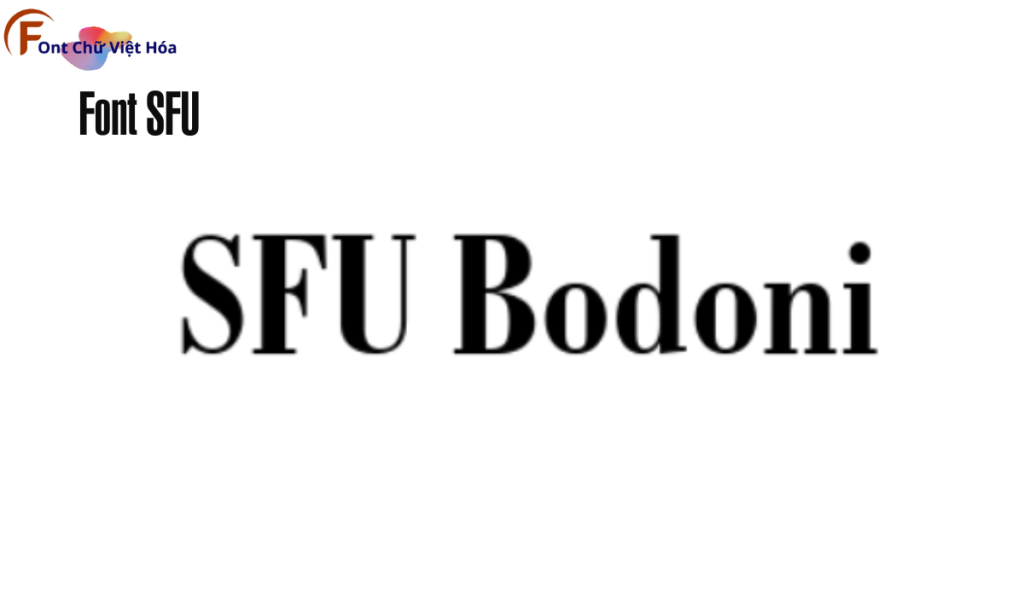
Font SFU Bodoni Việt Hóa
Phân loại: cổ điển, trang trọng
Kiểu chữ: chữ có chân
Độ dày: Regular, Bold, Italic
Font SFU Bodoni Việt Hóa, thuộc bộ font SFU, mang phong cách serif cổ điển với các đường nét thanh thoát và tinh tế. Font này được thiết kế nhằm mục tiêu tạo ra sự sang trọng và dễ đọc, đặc biệt phù hợp cho các thiết kế như sách, báo, và tài liệu. Đặc điểm hình dạng của SFU Bodoni là các đường nét rõ ràng và tỷ lệ chữ cân đối, giúp tạo ấn tượng thị giác mạnh mẽ và tối ưu hóa không gian trong thiết kế. Font này cũng đã được Việt hóa, mang đến sự linh hoạt và tiện dụng cho các dự án thiết kế bằng tiếng Việt, giúp người dùng dễ dàng tiếp cận và sử dụng.